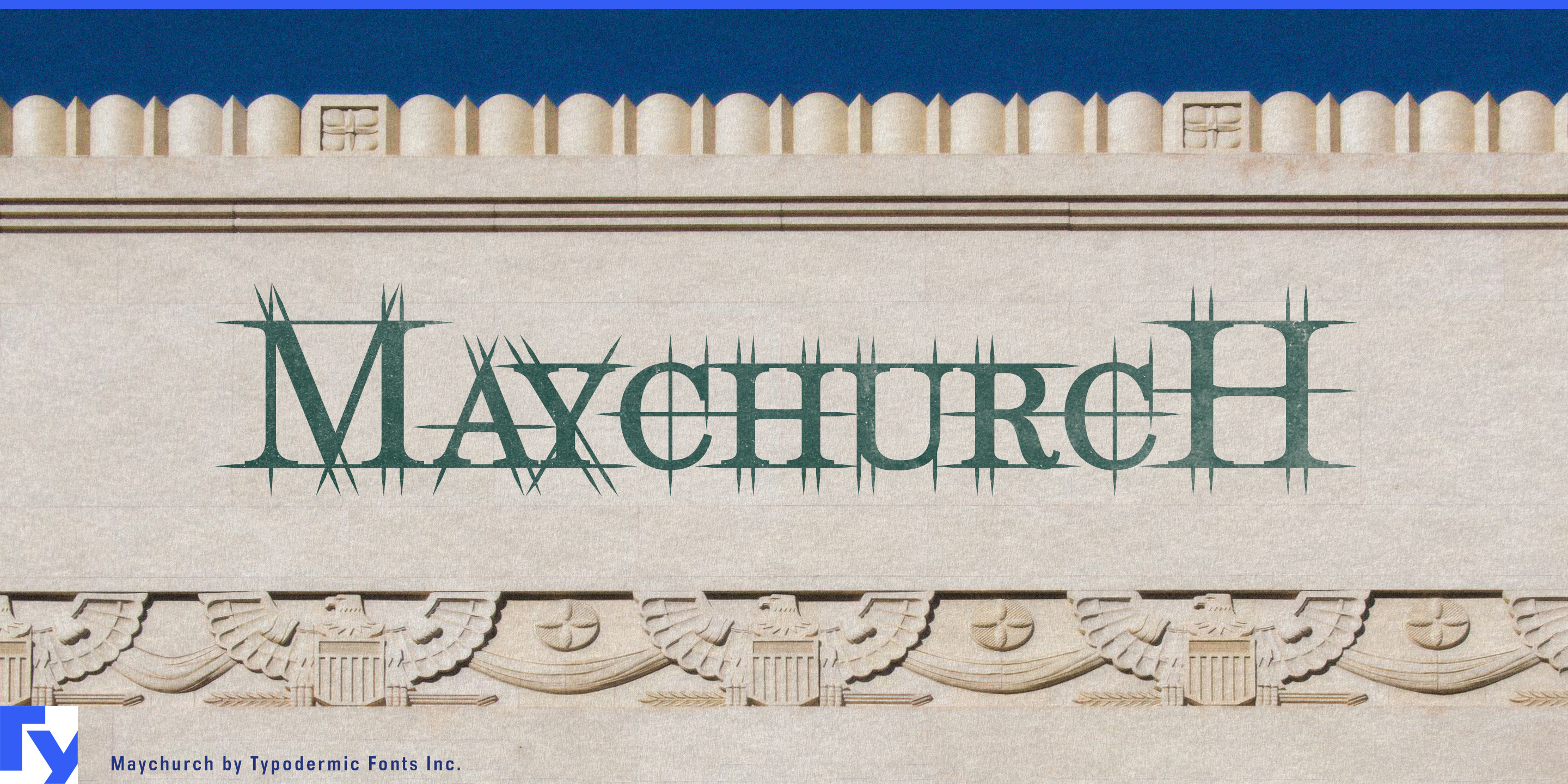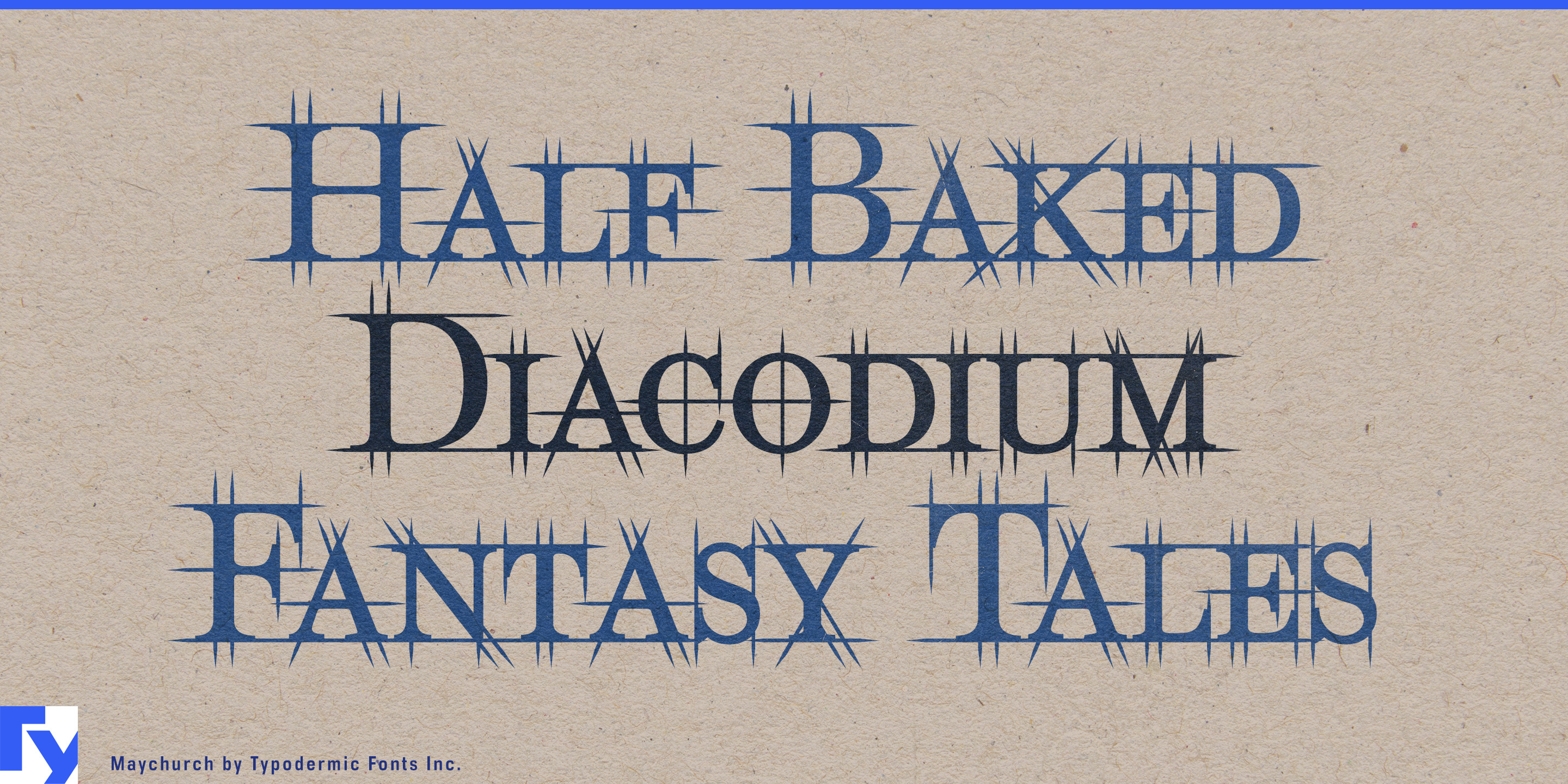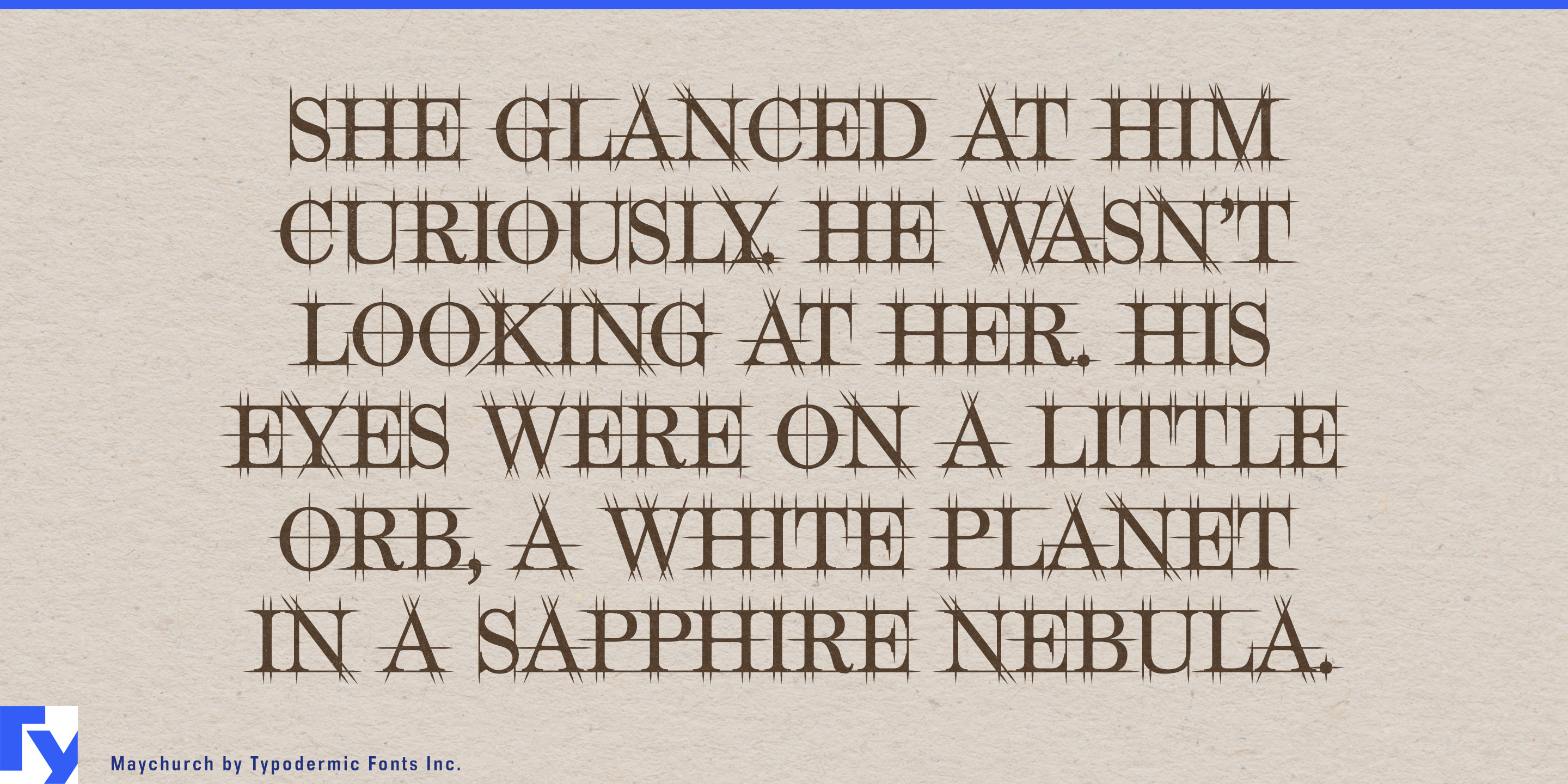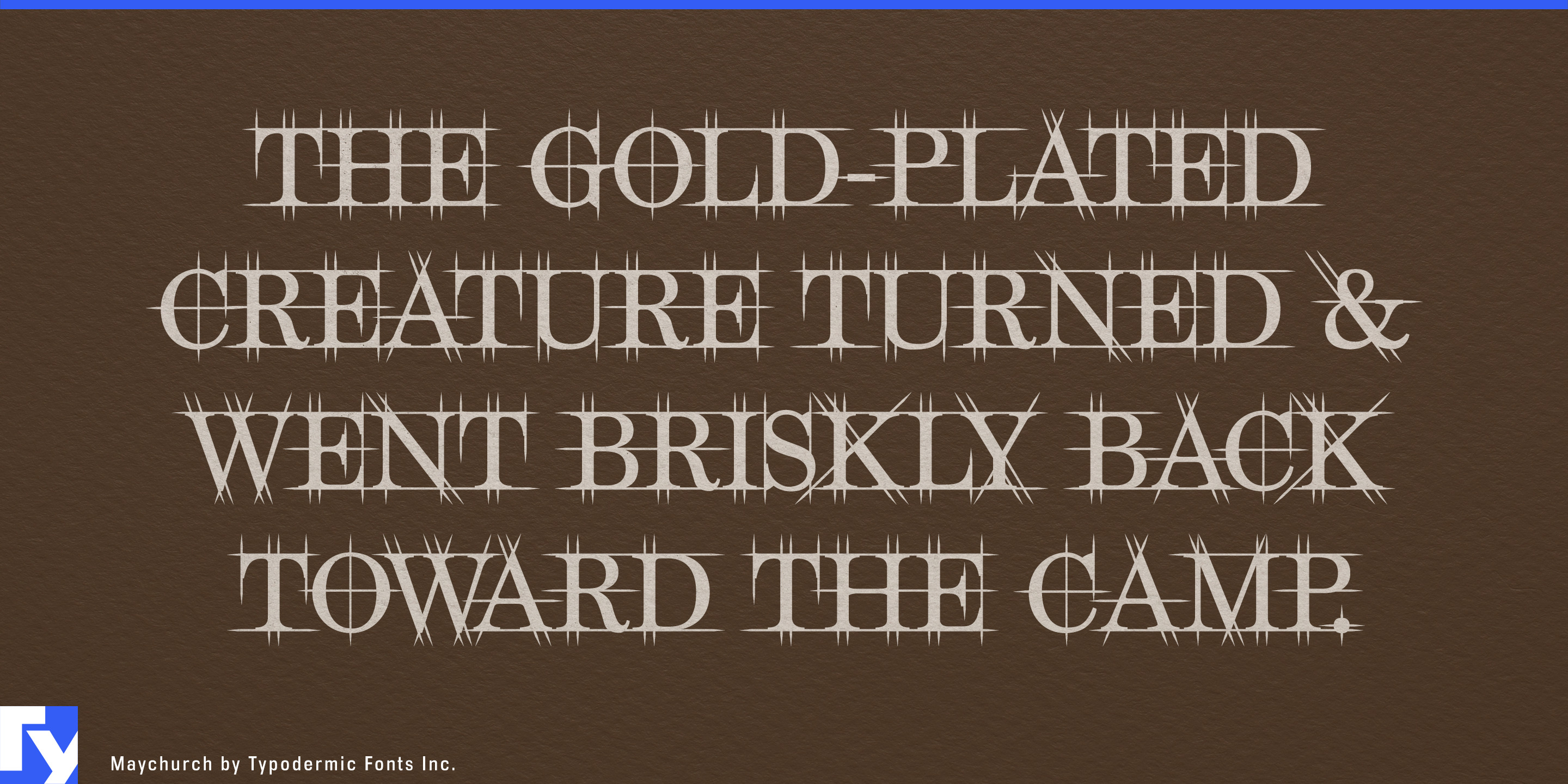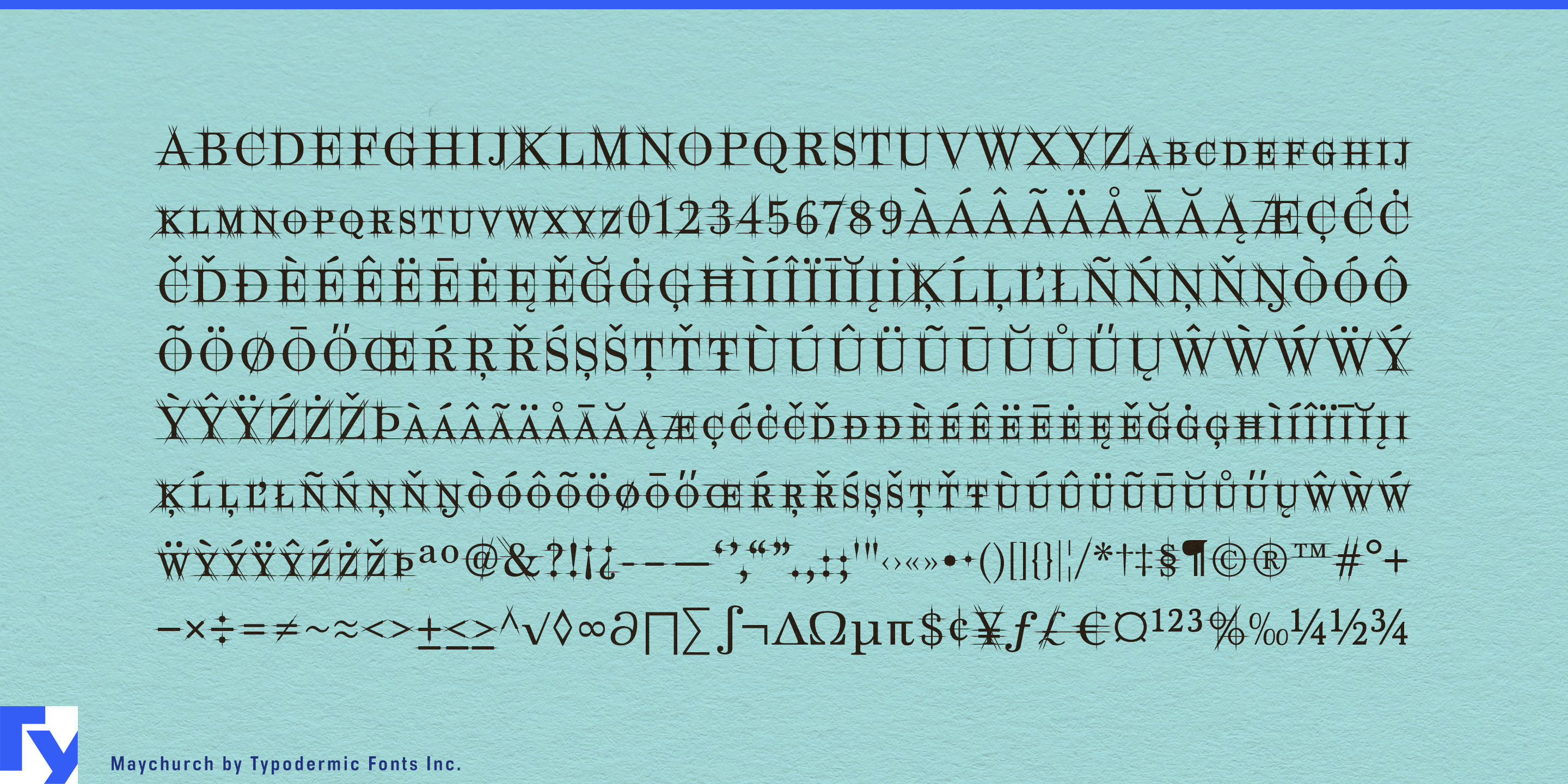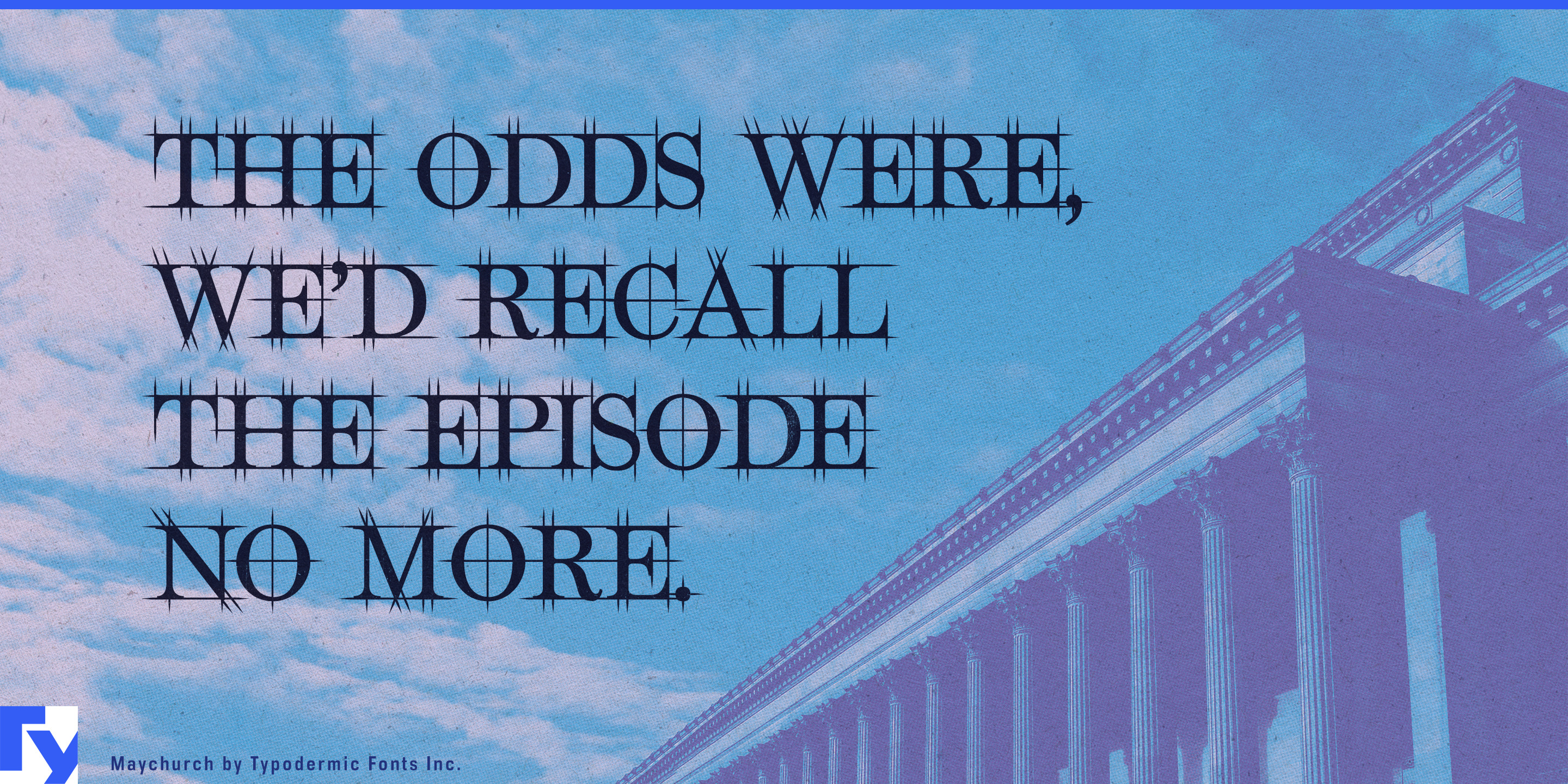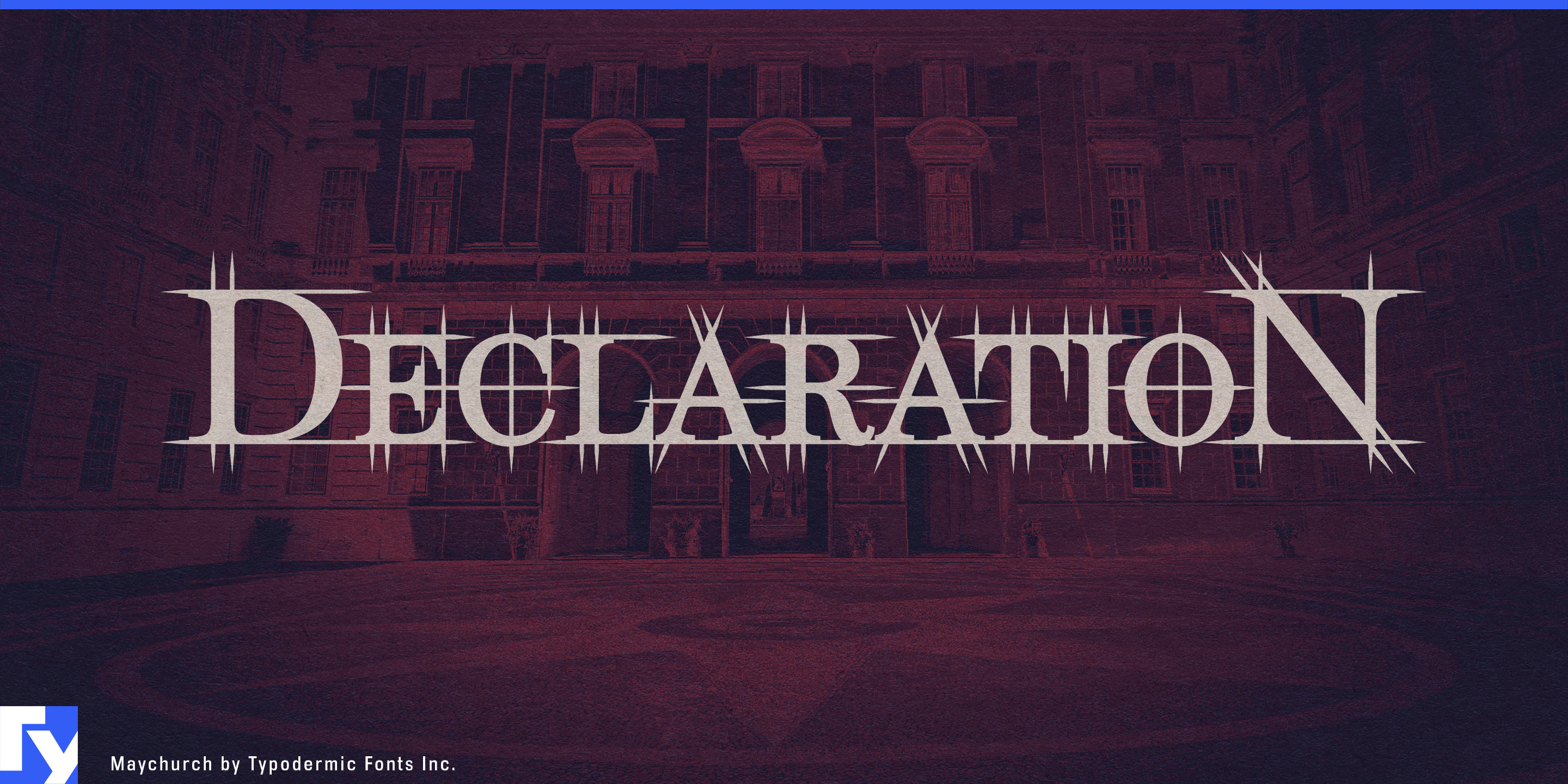
Maychurch
Architekturtypografie versucht oft, den Entwurfsprozess zu vermitteln, indem gewöhnliche Buchstaben mit Rastern, Kreisen, Maßlinien und Zeichenmarkierungen umgeben werden. Das Ergebnis kann wie Dekoration auf einer fertigen Überschrift wirken. Maychurch geht die Aufgabe aus dem Inneren der Buchstaben an. Klassische Serifenformen liegen unter einem bewusst fiktiven Netz geometrischer Konstruktionslinien. So sieht die Typografie aus, als würde sie auf dem Zeichenbrett noch vermessen, rationalisiert und ausgearbeitet.
Das macht Maychurch besonders nützlich für Architekturwettbewerbe und Vorstellungen großer Projekte. Architekturbüros, Projektentwickler und Visualisierungsstudios können sie für Projektnamen auf Wettbewerbstafeln, in Konzeptbüchern, Planungsausstellungen, an Wänden von Verkaufsgalerien und in Einführungsfilmen nutzen. Der zugrunde liegende Serifenaufbau hält die Verbindung zur Architekturtradition; die sichtbare Geometrie bringt Analyse und Konstruktion ein, ohne eine weitere Ebene scheinbar technischer Grafiken zu verlangen.
Massivholzbausysteme, Modulbau und vorgefertigte Bauteile bieten eine weitere starke Rolle. Werkseitig hergestellte Wohnbauten, Ingenieurholzkonstruktionen, Fassadensysteme und modulare Baugruppen stehen zwischen Architektur und Fertigung. Ihre Erscheinungsbilder müssen daher oft sowohl Gestaltungsabsicht als auch präzise Produktion vermitteln. Maychurch kann Systemnamen, Messewände, Katalogabschnittsanfänge und Einführungsgrafiken übernehmen, während eine zurückhaltende Sans Serif Maße, Spezifikationen und technische Tabellen trägt.
Architekturmaterialien profitieren von derselben Hierarchie. Kunststein, Architekturglas, Terrazzo, Konstruktionsholz, Metallgitter, präzise gefertigte Holzbauteile und individuelle Treppensysteme werden über Mustersammlungen, Spezifikationsbücher und Ausstellungsdisplays verkauft, in denen Materialcharakter und technische Glaubwürdigkeit zusammenkommen müssen. Maychurch kann einer Kollektion oder Produktfamilie eine architektonische Stimme geben, ohne vorzugeben, selbst die technische Information zu sein.
Die Erhaltung historischer Gebäude bietet einen besonders naheliegenden Spezialfall. Denkmalpflegearchitekten, Steinrestaurierungsfirmen, Ingenieure im Denkmalschutz und Fachleute für Bauaufmaße bearbeiten alte Formen mit heutiger Analyse. Titel von Restaurierungsprojekten, Aufmaßberichte, Grafiken auf Gerüstverkleidungen und Ausstellungen zur Denkmalpflege können mit Maychurch dieses Spannungsverhältnis direkt ausdrücken: klassisch wirkende Buchstaben, untersucht durch eine analytische geometrische Überlagerung.
Dieselbe Idee reicht in die computergestützte Fertigung hinein. Robotergestütztes Steinschneiden, CNC-Holzfertigung, digital erzeugte Fassaden, 3D-gedruckte Architekturbauteile und experimentelle Pavillons beruhen alle darauf, dass Geometrie zur physischen Struktur wird. Maychurch verbindet mit Architekturgeschichte assoziierte Serifenformen mit sichtbarer Konstruktionslogik, die zu Fertigungslaboren, Architekturbiennalen, Pavillonauftritten und Projektfilmen passt.
Die Geometrie ist bewusst erläuternd statt wörtlich. Sie legt kein verborgenes Rezept offen, nach dem die Buchstaben konstruiert wurden, sondern erinnert an die lange Tradition, Formen durch Kreise, Achsen und Proportionen rational zu erklären. Maychurch ist am nützlichsten, wenn ein Projekt neben dem fertigen Objekt auch das Denken, Messen und Konstruieren dahinter zeigen soll.